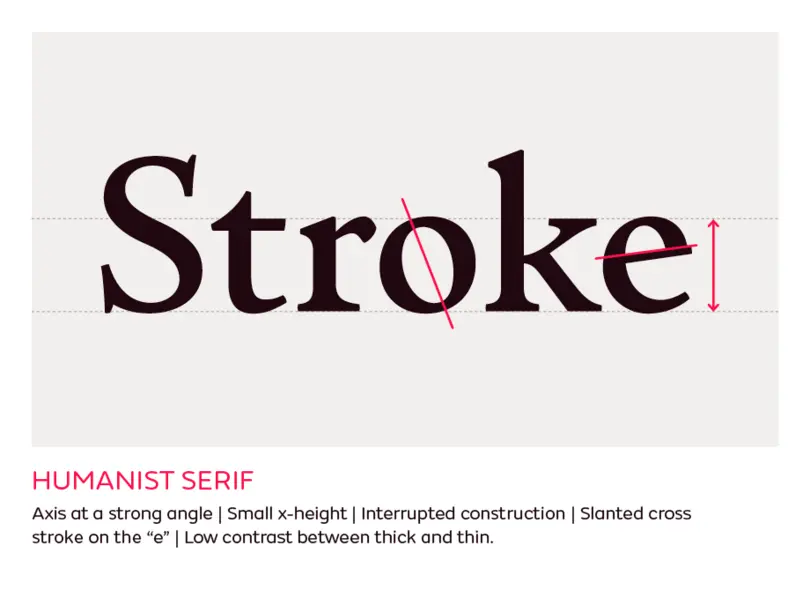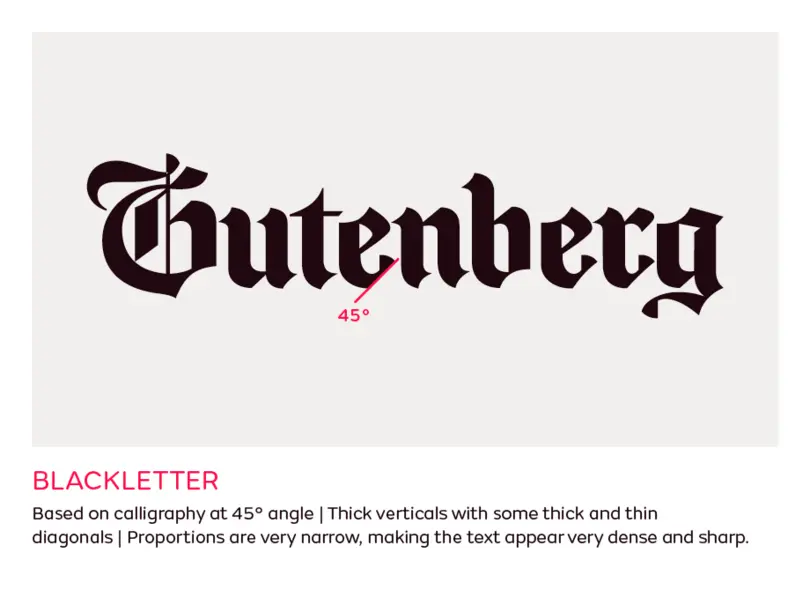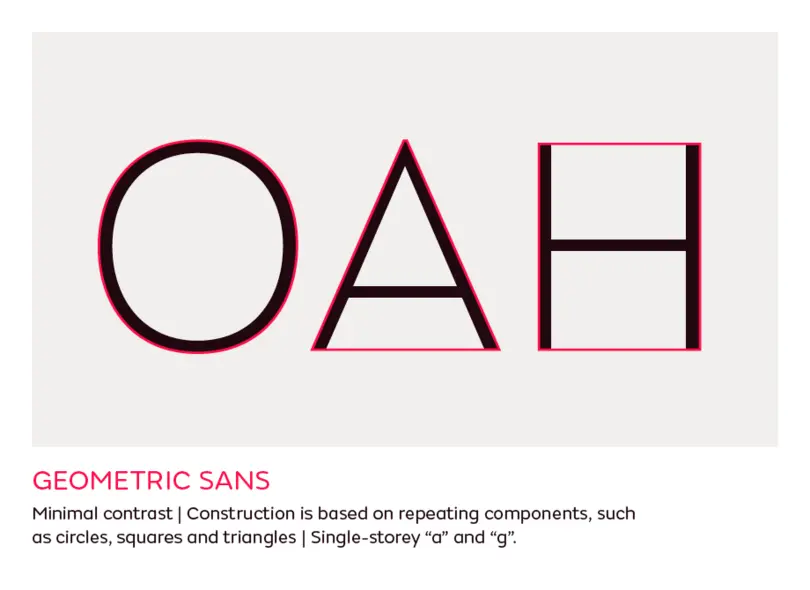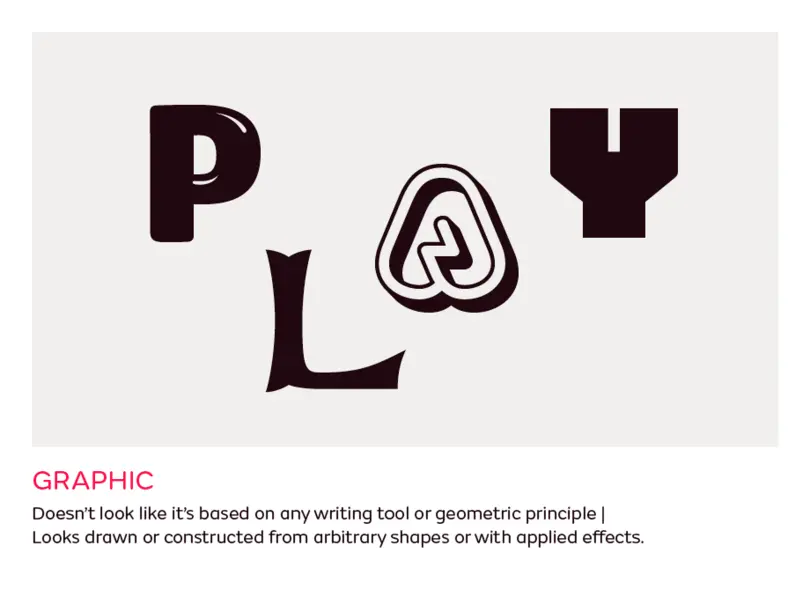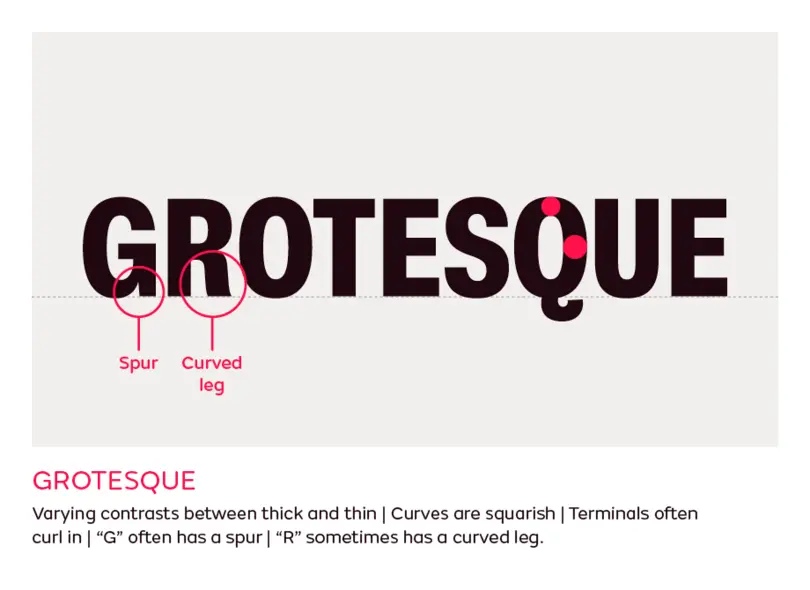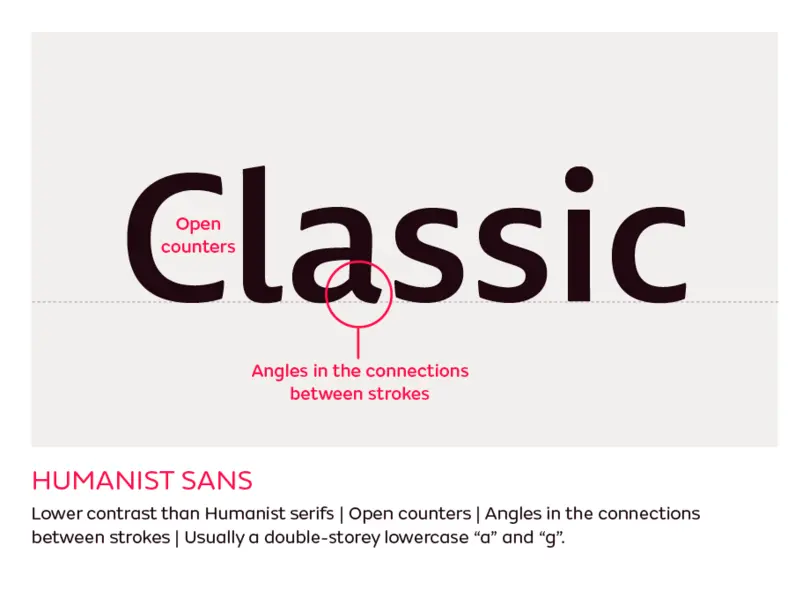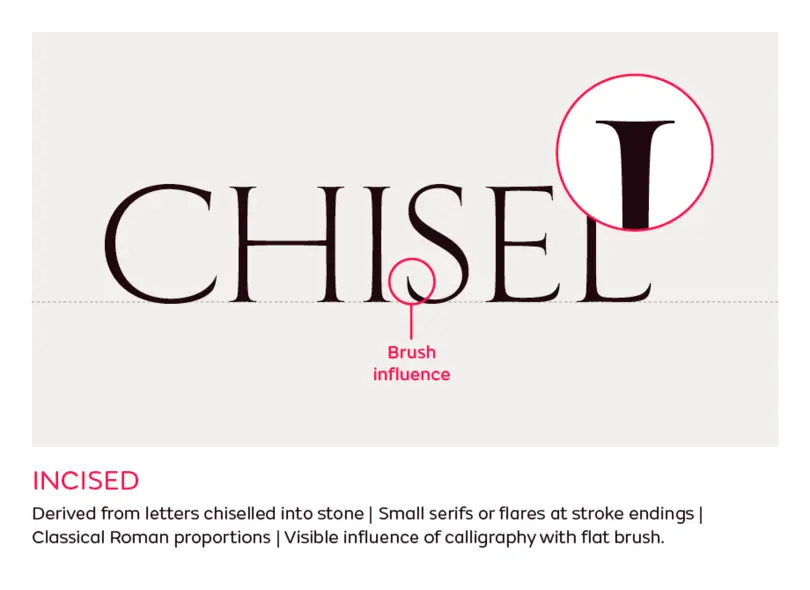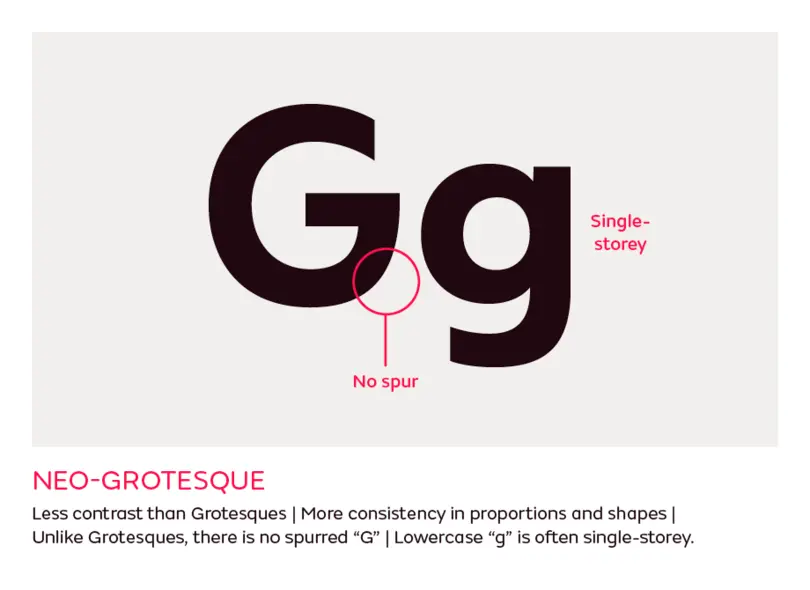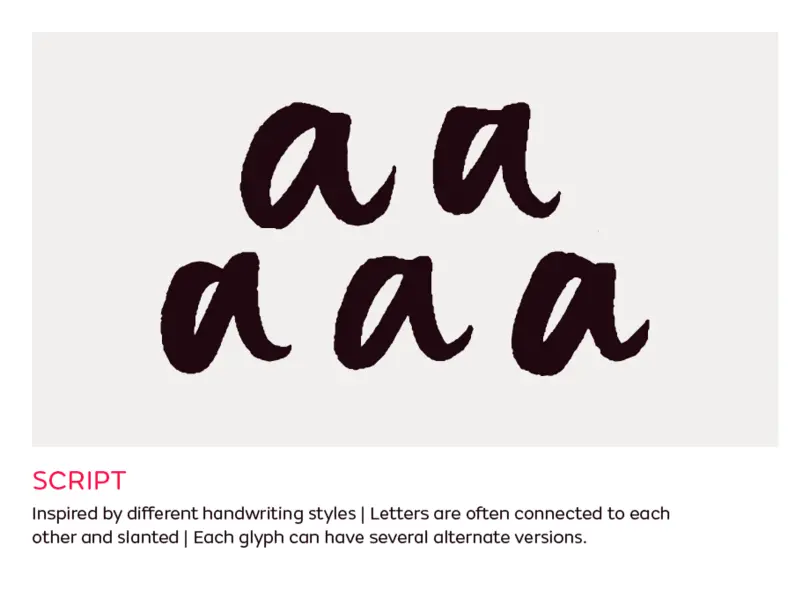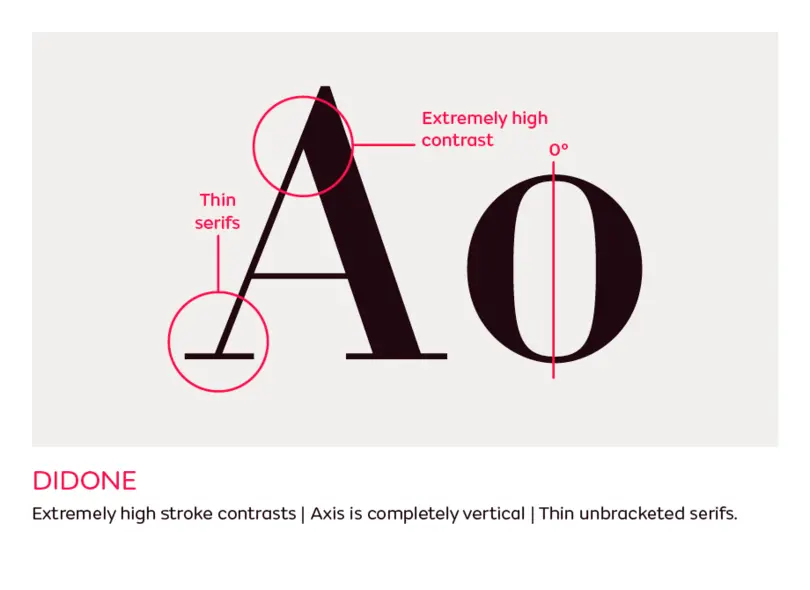
Wegweiser durch die Schriftstile.
Wenn es um allgemein bekannte Schriftstile geht, denken die meisten Menschen an Sans, Serif, Script und vielleicht noch an Slab. Vier Schriftgenres wären einfach und leicht zu verstehen, aber sie würden das Design auch nicht wirklich spannend machen. Zum Glück gibt es ganz viel mehr Schriftklassen und Unterklassen, die es zu entdecken gilt.
In der Geschichte der Schrift gab es schon immer Versuche, die Vielfalt der Schriften zu klassifizieren. Manche Systeme basierten auf historische Epochen, andere auf den visuellen Eigenschaften einer Schrift, und wieder andere auf einer Kombination aus beidem. Eines der außergewöhnlichen Klassifizierungssysteme ist Official Vox/ATypI, eine Mischung aus historischen Begriffen und visuellen Attributen, dessen Unterstützung die  ATypI 2021 allerdings wieder zurückzog. British Standard ist eine vereinfachte Version von Vox, während die Gerrit-Noordzij-Theorie besagt, dass jede Schrift auf das Handschrift-Werkzeug zurückgeführt werden kann, auf dem sie basiert. Sie alle eliminieren die Probleme der rein historischen Klassifizierungen, fallen aber in sich zusammen, wenn Schriften Merkmale außerhalb der vorgegebenen Parameter aufweisen.
Die meisten der Klassifizierungssysteme gelten entweder als veraltet, oder als zu subjektiv oder als verwirrend. Tatsächlich ist das Schriftdesign eine vielfältige Disziplin mit der Tendenz, neue Varianten zu kreieren. Viele zeitgenössische Schriften passen in keine der historischen Kategorien, sodass es inzwischen als unmöglich gilt, ein System zu entwickeln, das alle Spielarten des Schriftdesigns erfasst.
Ein Verständnis für die Geschichte des Schriftdesigns hilft Designerinnen und Designern allerdings, bessere Entscheidungen zu treffen, etwa bei der Kombination von Schriften oder bei der Suche nach dem richtigen Stil für ein Logo oder eine Beschriftung. Die Kenntnis der historischen Konnotationen bestimmter Stile oder einfach ihrer visuellen Merkmale kann bei solchen Jobs von unschätzbarem Wert sein.
Wenn Sie die grundlegende Klassifizierung verstehen, hilft Ihnen das auch weiter, subtilere Unterschiede innerhalb und außerhalb einer Stilklasse zu erkennen. Es hilft auch, wenn Sie Ihrem Auftraggeber die Wahl für eine Schrift begründen oder einen Exklusiventwurf in Auftrag geben. Und es bereichert ganz einfach Ihre Design-Kompetenz.
Anstatt die bestehenden Klassifizierungen zu interpretieren oder ein neues System zu entwickeln, versucht unser Leitfaden, die populärsten Stilbegriffe der Schriftenwelt zu entmystifizieren, damit Sie die meistgenutzten Bezeichnungen in der latein-basierten Typografie sicher verwenden können.
Serifs
Humanist
The first Roman type was derived from calligraphy, so the shape of letterforms is based on formal writing with a flat brush or a broad nib pen. The term Humanist has traditionally been used for serif typefaces, but nowadays there is also Humanist Sans.
Beispiele: Centaur, Adobe Jenson, Cloister, Guardi, Lutetia, Lynton, Stempel Schneidler
Garalde
Ein Kunstwort, zusammengebaut aus den Namen der zwei bedeutendsten Schriftschöpfern der Zeit zwischen dem späten 14. und dem 17. Jahrhundert, dem französischen Stempelschneider Claude Garamond und dem venezianischen Drucker Aldus Manutius. Im Deutschen auch französische Renaissance-Antiqua genannt. Die Unterklasse der Garamond-Schriften ist eine Weiterentwicklung der humanistischen Schriften und stehen noch immer unter dem Einfluss der formalen Kalligrafie. Zahlreiche technische Verbesserungen beim Druck und dem Stempelschneiden zu dieser Zeit erlaubten die Verfeinerung und Herstellung neuer Varianten, oder Wiederauflagen, die noch heute für den Satz von Büchern oder langen Texten eingesetzt werden.  Sie laufen auch unter der Bezeichnung  Aldine, nach Aldus Manutius. Im englischen Sprachraum hat sich auch Old-style durchgesetzt, wobei diese Bezeichnung auch gerne für alle humanistischen, Garalde- und Transitional-Schriften verwendet wird.
Merkmale: Raffinierte Proportionen, ein stärkerer Kontrast zwischen dick und dünn, aber in einem gemäßigteren Winkel, die Serifen haben eine definierte Form, der mittlere Strich des Kleinbuchstabens e ist horizontal.
Beispiele: Garamond, Bembo, Janson, Palatino, Galliard, Caslon, FS Brabo
Transitional
Auch: vorklassizistische Antiqua. Ende des 17. Jahrhunderts wollte Ludwig XIV. die Druckerei der französischen Regierung (die Imprimerie Royale) neu ausrichten, um einen Ersatz für Garamond zu finden und mit der Entwicklung und Qualität des Drucks in ganz Europa zu konkurrieren. Er beauftragte die französische Akademie der Wissenschaften, eine neue Schrift für ihn zu entwerfen. Das Ergebnis war die „Roman du Roi“: 86 Schnitte, die nach einem strengen System von Rastern, Mathematik und Technik entworfen wurden. Bekannte Schriftgestalter zu dieser Zeit waren John Baskerville, Simon Fournier und Christophe Plantin. Eine andere Bezeichnung für die Transitional ist Realist, hergeleitet vom spanischen Begriff für königlich, und auf die von Plantin für den spanischen König Phillip II. entworfene Schrift zurückgeht.
Merkmale: Der Kontrast ist noch stärker als bei den ersten beiden Gruppen. Die unterschiedliche Strichstärke zwischen den Vertikalen und Horizontalen  ist stärker ausgeprägt, Haar- und Grundstriche sind unterschiedlich breit. Die Serifen sind flacher, und die Details sind sehr raffiniert. Transitional-Schriften sind leicht zu erkennen, wenn man sie als „Übergang“ zwischen Old-Style und den modernen Schriften betrachtet.
Beispiele: Baskerville, Fournier, FS Neruda, FS Sally, Joanna, Melior, Times
Didone
Auch: klassizistische Antiqua. Der Begriff Didone leitet sich von den Namen der Schriftgießereigründer Firmin Didot und Giambattista Bodoni ab. Sie waren beide begabte Handwerker und haben durch ihre berufliche Rivalität die Grenzen des Schriftdesigns, des Stempelschneidens und des Druckens verschoben. Auch bekannt als Modern – kein besonders hilfreicher Name, da er mit Adjektiven wie „modern“ oder „zeitgenössisch“ verwechselt werden kann.
Merkmale: Man könnte sie fast mit den kalligrafisch entwickelten Serifs verwechseln, doch die Formen der gemeißelten Schriften leiten sich von der Verwendung eines Meißels ab, mit dem die Buchstaben in Stein geschlagen wurden. In diesem Fall sind die Serifen das Ergebnis eines Handwerks und kein Gestaltungsmerkmal. Und sie sind in der Regel kleiner, manchmal sogar reduziert auf einen Einschnitt am Strichende.
Beispiele: Trajan, FS Rom, Fritz Quadrata, Albertus, FS Benjamin, Lithos, Exocet